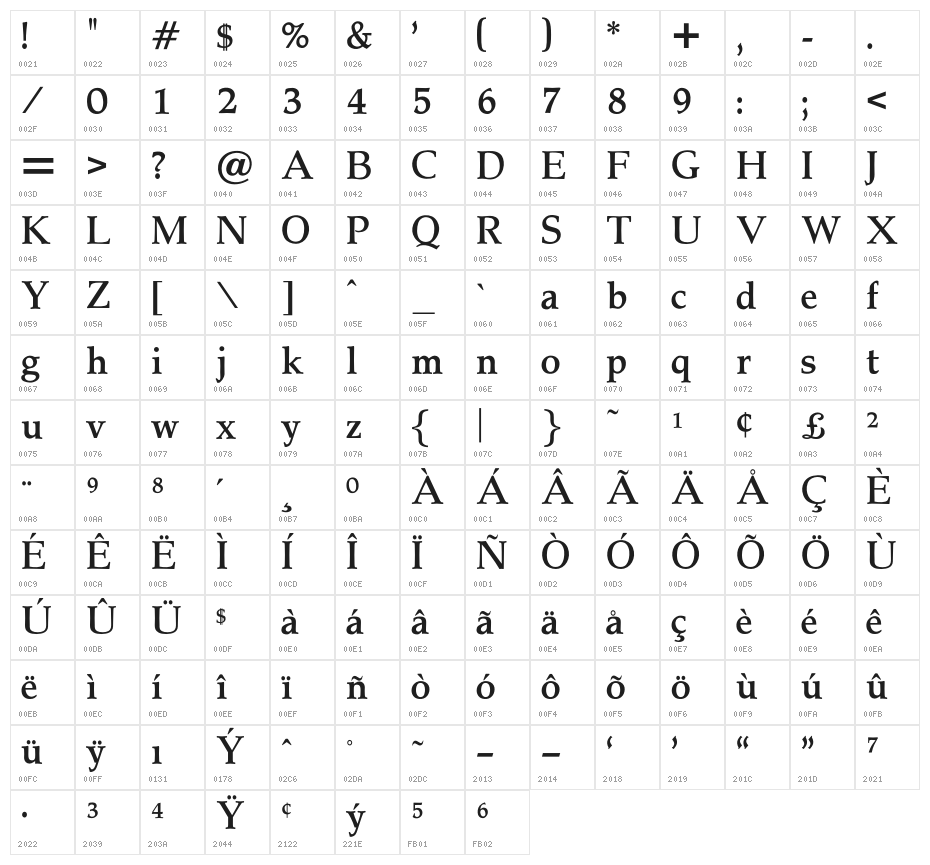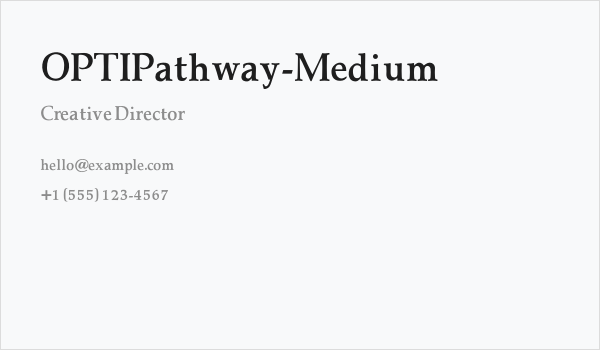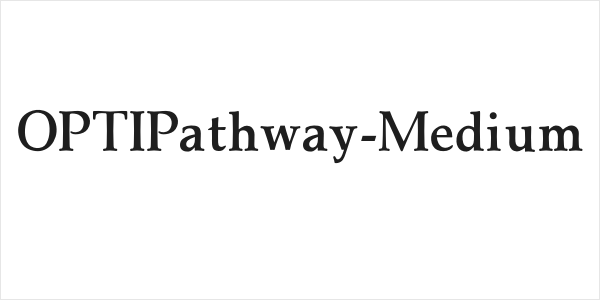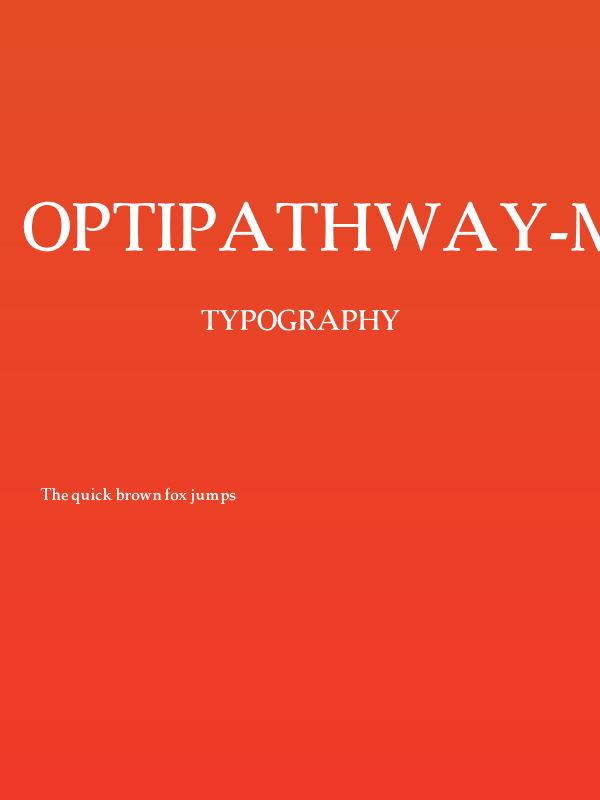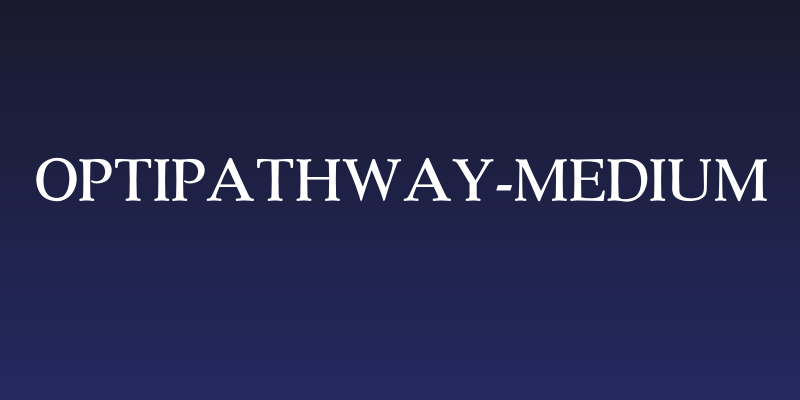
OPTIPathway-Medium Font
✎ Serif
| Progetti proposti | Ideal for editorial design, book covers, formal invitations, and branding projects that require a classic and elegant touch. |